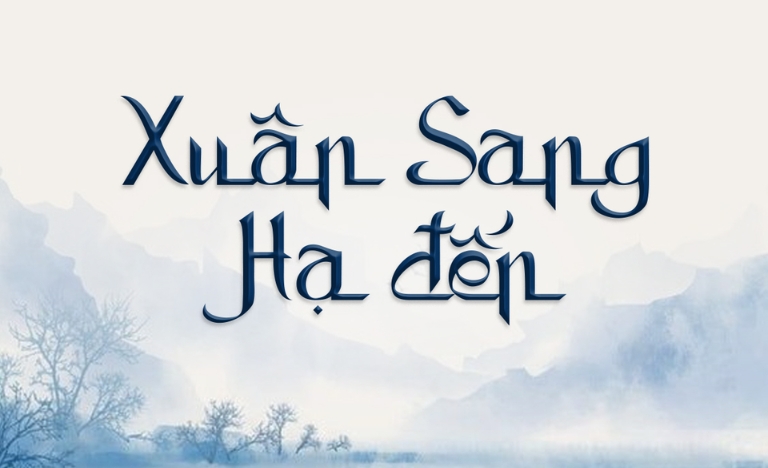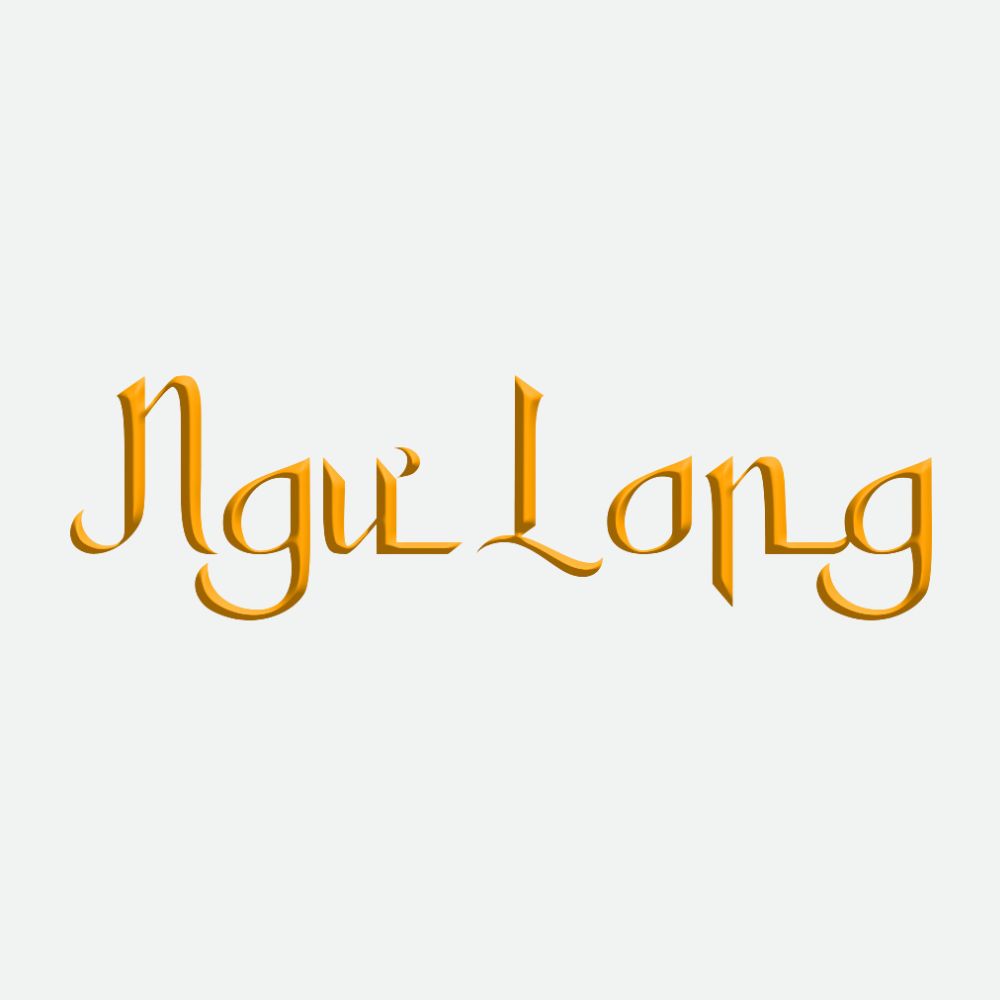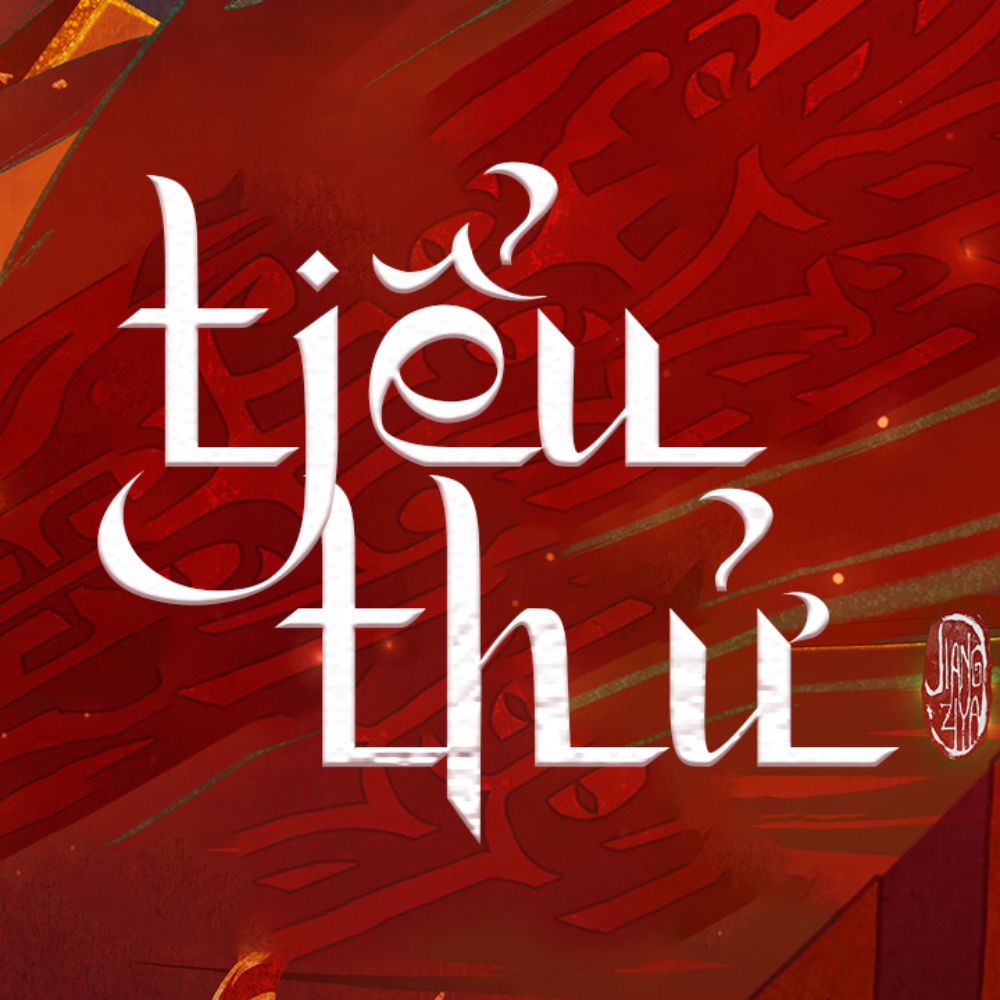
Trong các thiết kế mang hơi hướng Á Đông hoặc phong cách hoài cổ, việc lựa chọn kiểu chữ đóng vai trò then chốt để tạo nên linh hồn cho tác phẩm. Font cổ trang Việt hóa Zahra là một trong những bộ font giả bút lông đầy nghệ thuật, mang lại vẻ đẹp thanh tao nhưng không kém phần mạnh mẽ.
Đặc điểm thẩm mỹ độc đáo của font cổ trang Việt hóa Zahra
Zahra thu hút người nhìn bởi những nét cọ dày mỏng đan xen nhịp nhàng, mô phỏng sinh động kỹ thuật viết thư pháp truyền thống. Các đường nét được thiết kế có độ bay bổng và phóng khoáng, giúp tạo ra cảm giác thư thái và cổ điển cho người xem. Phiên bản font chữ cổ trang Việt hóa Zahra đã được tinh chỉnh phần dấu tiếng Việt một cách tỉ mỉ, giúp các dấu thanh không bị tách rời hay làm hỏng cấu trúc ký tự gốc.
Bên cạnh yếu tố thẩm mỹ, Zahra còn sở hữu khả năng hiển thị khá ấn tượng trên các chất liệu in ấn khác nhau. Dù được sử dụng trên nền giấy mỹ thuật, gỗ hay kim loại, bộ font này vẫn giữ được sự chỉn chu và rõ nét. Đây là phương án phù hợp để truyền tải những thông điệp mang tính nghệ thuật cao, giúp bản thiết kế thoát khỏi sự đơn điệu của các font chữ hệ thống thông thường.
Thông số kỹ thuật và link tải font chữ cổ trang Việt hóa Zahra
| Phân loại phong cách | Cổ trang / Brush Script |
| Mục đích phù hợp | Tiêu đề, Bảng hiệu, Poster hoài cổ |
| Nguồn gốc | Đã được Việt hóa và xử lý dấu |
Gợi ý phối hợp: Font Zahra có nét chữ khá dày và giàu tính trang trí. Bạn nên phối hợp nó cùng các font không chân (Sans-serif) đơn giản cho phần nội dung chi tiết để tạo sự cân bằng về thị giác, giúp người xem không bị rối mắt.
03 Ứng dụng font việt hóa cổ trang Zahra vào không gian kiến trúc
Với vẻ ngoài đậm chất nghệ thuật, bộ font chữ này mang lại giá trị cao khi được đưa vào thực tế trang trí và quảng bá các công trình mang phong cách Zen hoặc Vintage:
- Bảng tên khu nghỉ dưỡng và Homestay: Những nét chữ thư pháp của Zahra rất ăn ý khi xuất hiện trên các biển hiệu gỗ hoặc đá tự nhiên. Đối với các dự án nhà lắp ghép mang phong cách mộc mạc, font chữ này giúp không gian trở nên gần gũi và có chiều sâu văn hóa.
- Thiết kế Menu và Voucher cho trà quán: Sử dụng Zahra cho các tiêu đề chính trên thực đơn giúp khơi gợi cảm hứng về một không gian thư giãn, yên bình, rất dễ tạo thiện cảm với khách hàng yêu thích nét đẹp truyền thống.
- Trang trí nội thất và Quotes treo tường: Bạn có thể dùng font Zahra để cắt chữ nổi laser trang trí tại các phòng trà, phòng đọc sách hoặc không gian thiền định nhằm tạo điểm nhấn đầy tinh tế cho mảng tường.
03 Lưu ý khi sử dụng font việt hóa cổ trang Zahra để bố cục hài hòa
Để khai thác hiệu quả vẻ đẹp của font việt hóa cổ trang Zahra mà không làm hỏng bố cục chung, người thiết kế nên lưu tâm một số điểm sau:
- Ưu tiên làm tiêu đề: Do nét chữ uốn lượn và dày, Zahra chỉ nên xuất hiện ở các vị trí tiêu đề lớn hoặc slogan ngắn. Việc sử dụng font này cho các đoạn văn bản dài sẽ gây khó đọc và tạo cảm giác nặng nề.
- Kiểm soát khoảng cách dòng: Các nét móc của Zahra thường vươn rộng ra xung quanh. Bạn cần nới rộng khoảng cách giữa các dòng để các ký tự không bị chồng chéo lên nhau, giữ được sự thông thoáng cần thiết.
- Lựa chọn màu sắc tinh tế: Font phong cách cổ trang sẽ trông sang trọng hơn khi sử dụng các tông màu trầm như đen mực tàu, đỏ bordeaux, hoặc vàng đồng trên nền giấy tối màu hoặc vật liệu tự nhiên.